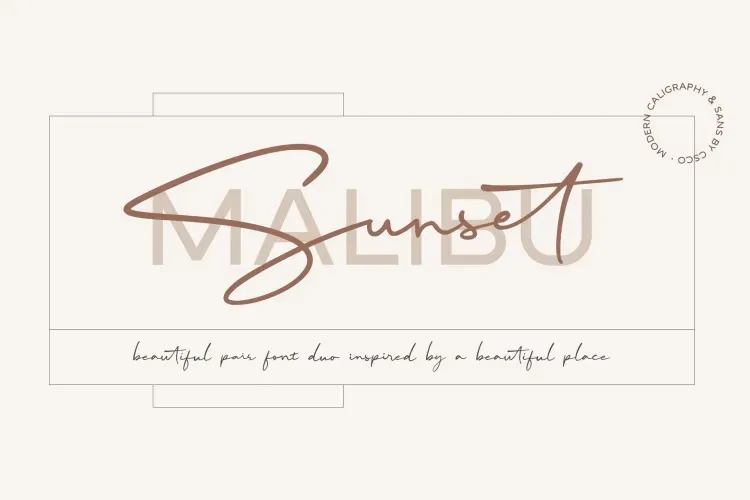
Malibu Sunset Font Duo – Fonte Grátis
Malibu Sunset Font Duo
Esta font ‘Malibu Sunset Font Duo’ é uma combinação perfeita entre a elegância dos sinóticos sem serif e a personalidade do script livremente escrito. O conjunto contém dois tipos de fontes, um moderno e delicado tipo sinótico sans-serif e uma escrita em estilo livre que carrega o encanto da praia californiana chamada Malibu. A inspiração se deriva dos desenhos exuberantes do entardecer sobre as ondas pacatas da costa de Malibu, um lugar conhecido por sua sofisticação e estilo único. A Malibu Sunset Font Duo será perfeita para qualquer tipo de marca, desde marcas de moda até blogs de tendências, boutique de casamentos, ou mesmo empresas que desejam adquirir uma aparência atraente e chique.